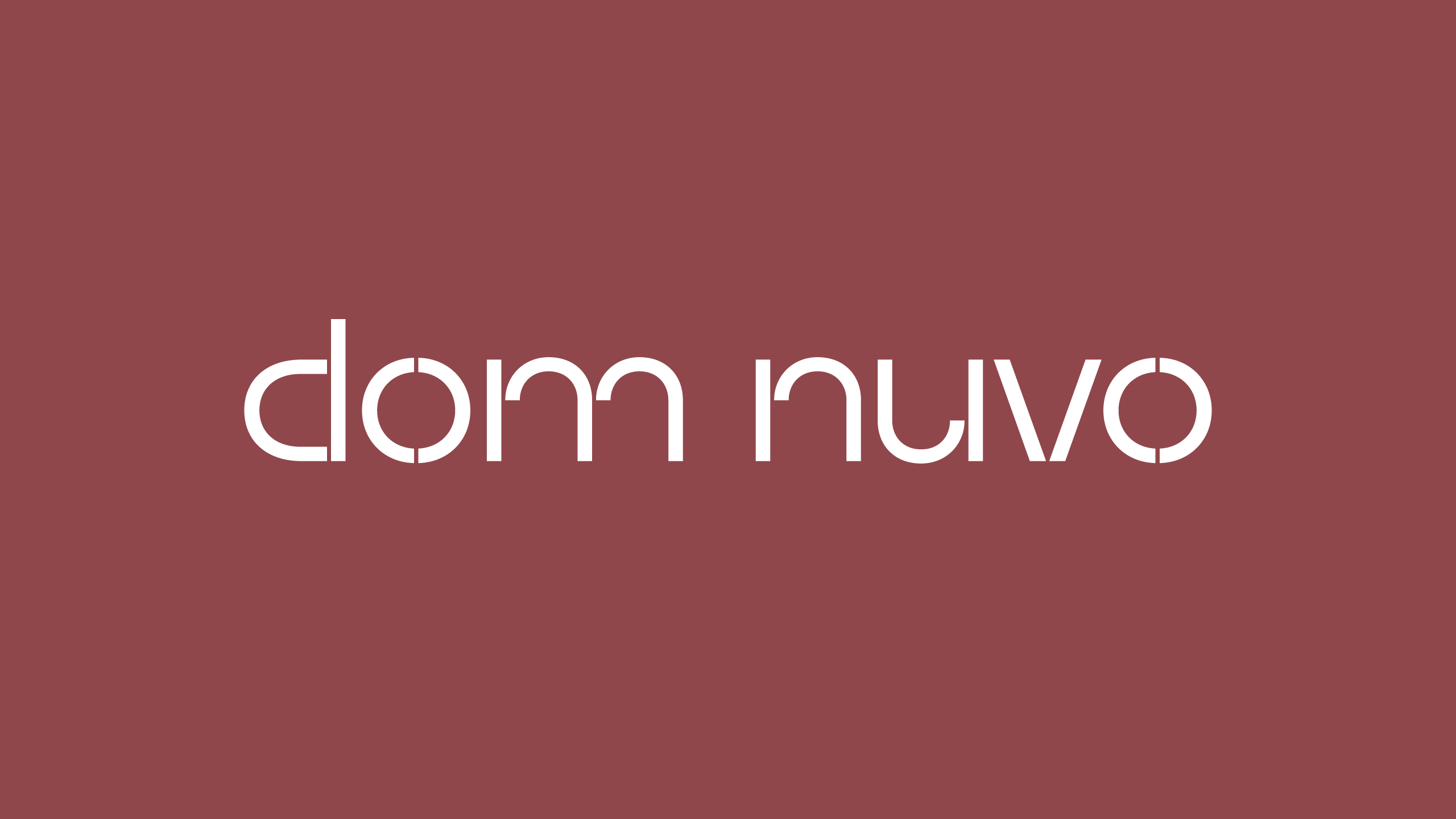
Dom Nuvo
Logo pre polyfunkčnú budovu Dom Nuvo od architektonického štúdia Archekta v Čadci. Modulárne sans-serifové logo symbolizuje polyfunkčnosť a verzatilitu budovy.